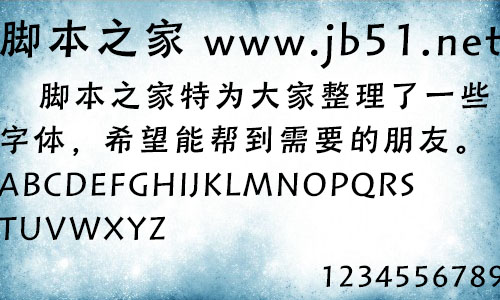
漢儀瑞云袖舞65W一款不錯(cuò)的藝術(shù)字體,由漢儀字庫出品,字體筆觸略粗,字形排版略顯傾斜,具有很好的視覺感,適合應(yīng)用于藝術(shù)設(shè)計(jì)、平面宣傳設(shè)計(jì)、網(wǎng)頁設(shè)計(jì),書法字帖等領(lǐng)域,需要的朋友可以前來本站下載。